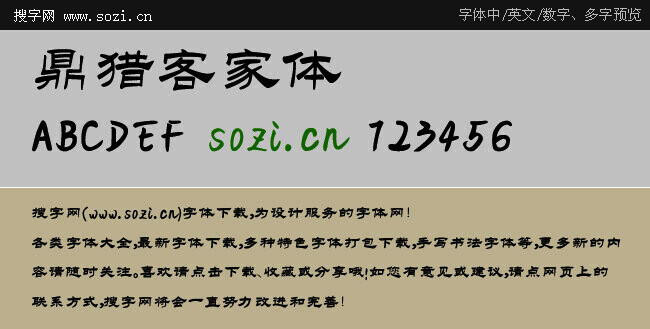
鼎猎客家体
搜字网提供一款鼎猎客家体中文艺术字体下载,鼎猎客家体以富有中国文化底蕴距今1600年魏晋南北朝时期社会流行字体爨体字体为参照,爨体字所具有的古韵、浑厚、拙朴特质,与客家文化相互交融。由此碰撞出专属于客家人的鼎猎客家体。是一套根据简体中文汉字编码国家标准(GB2312编码)设计的字体,并在此基础上一共设计了6789个简体汉字。字体适合海报设计、广告创意、包装设计等应用。